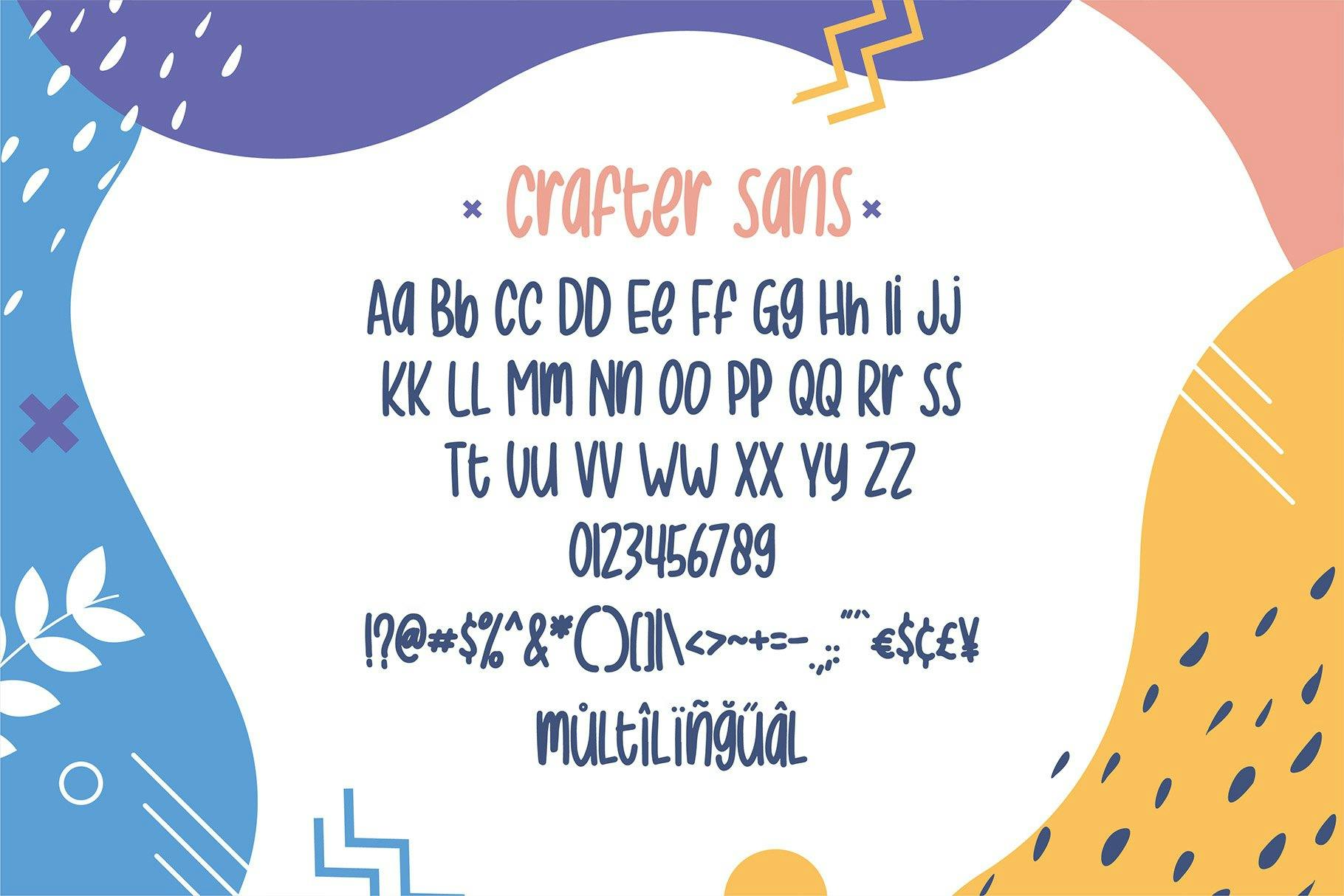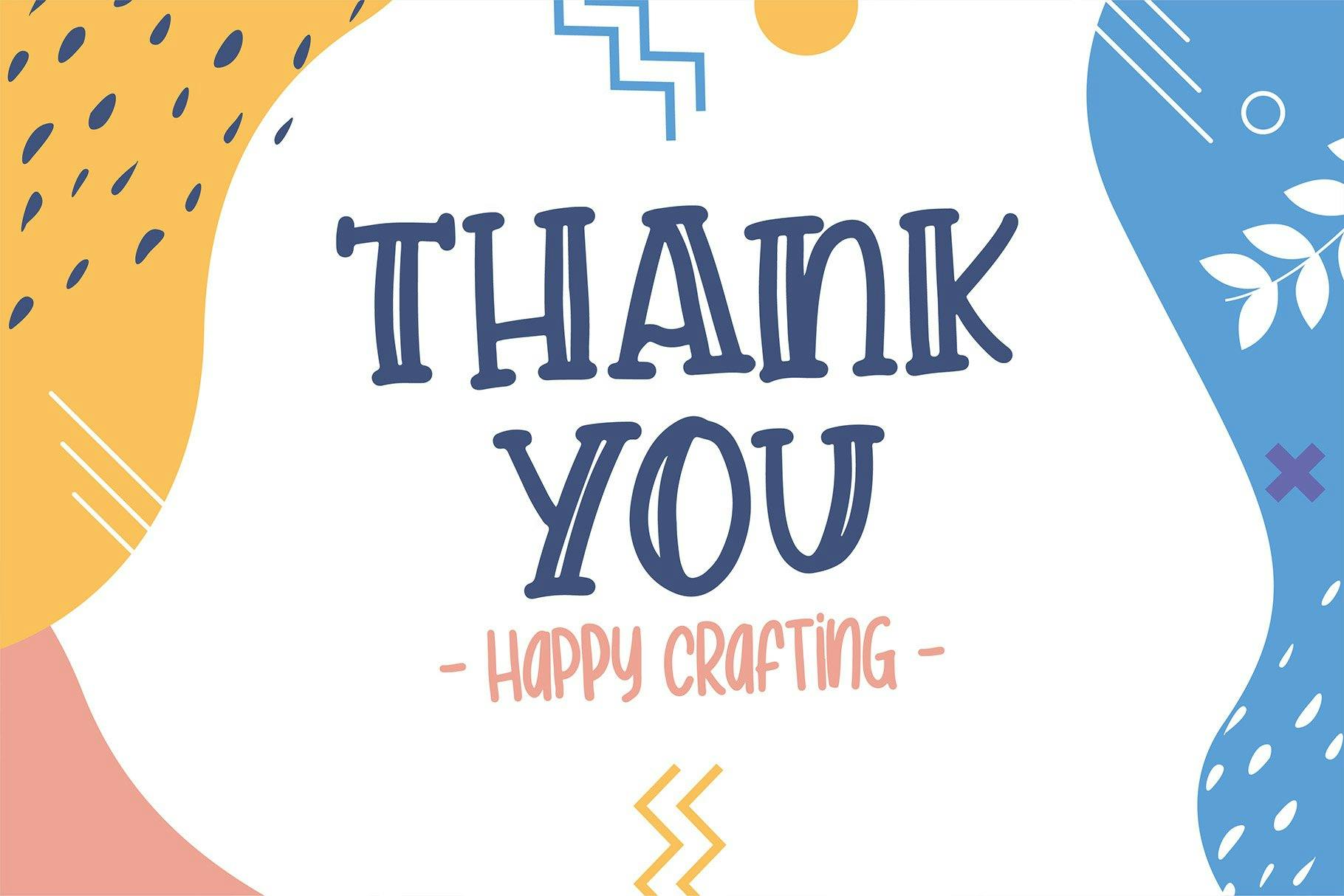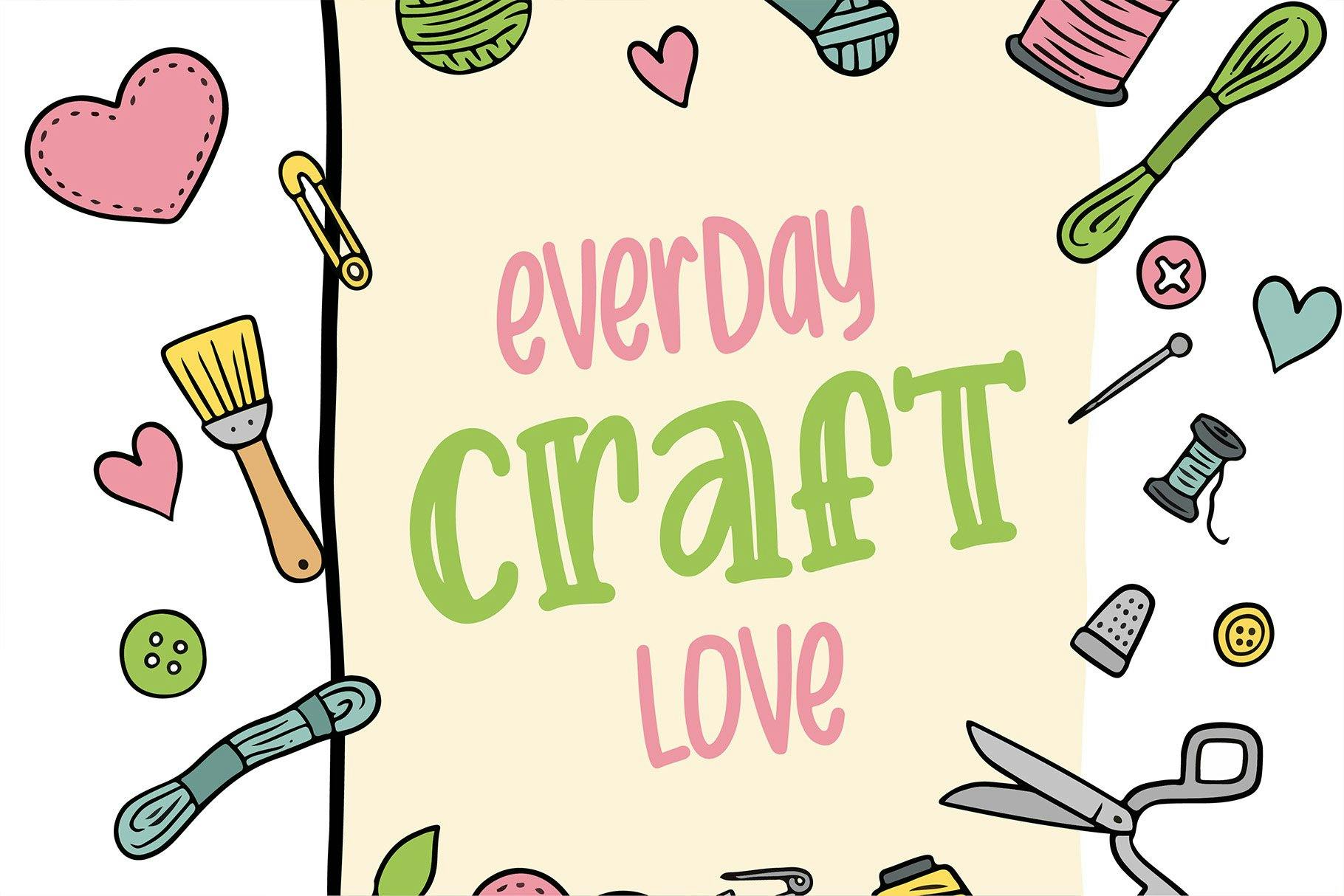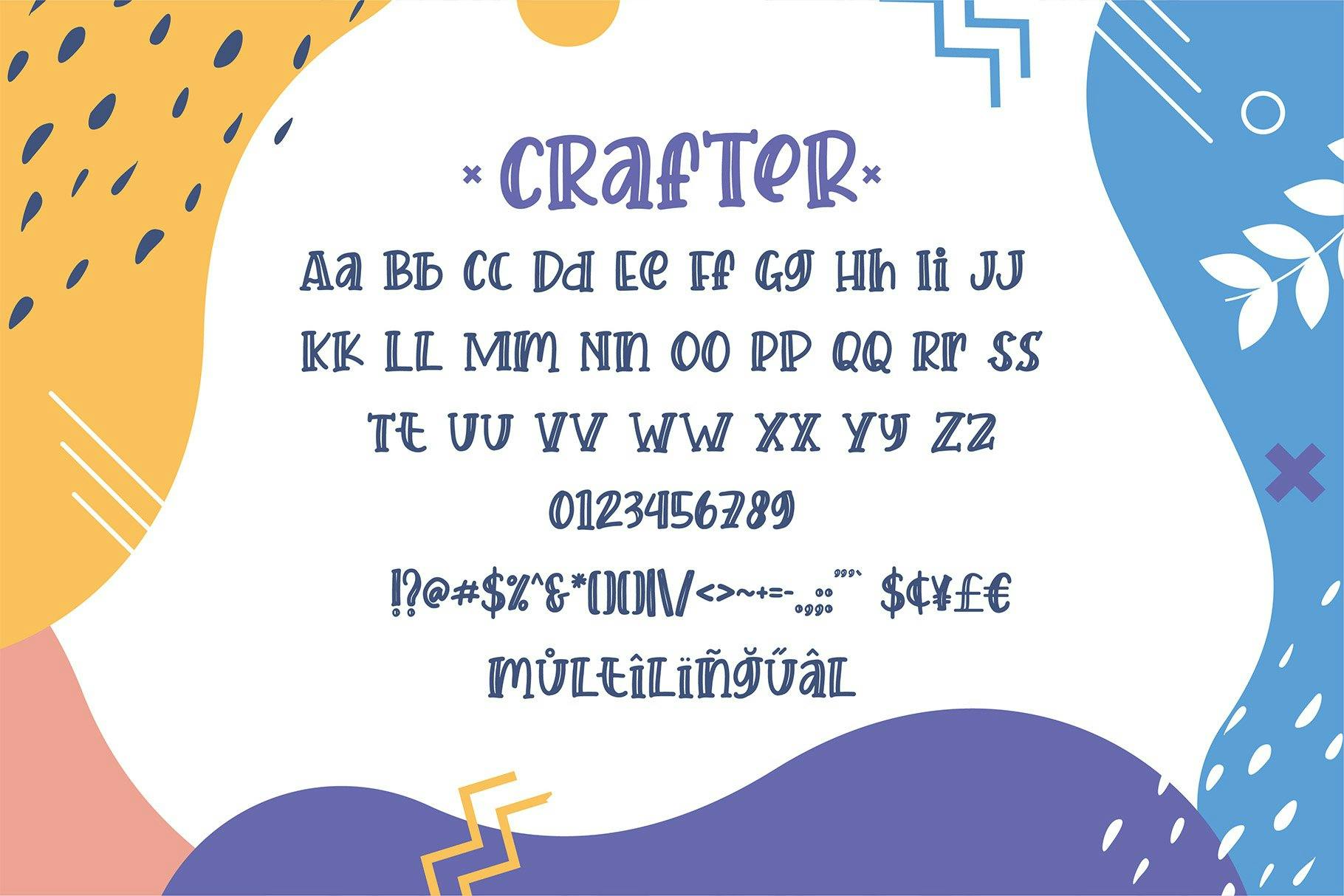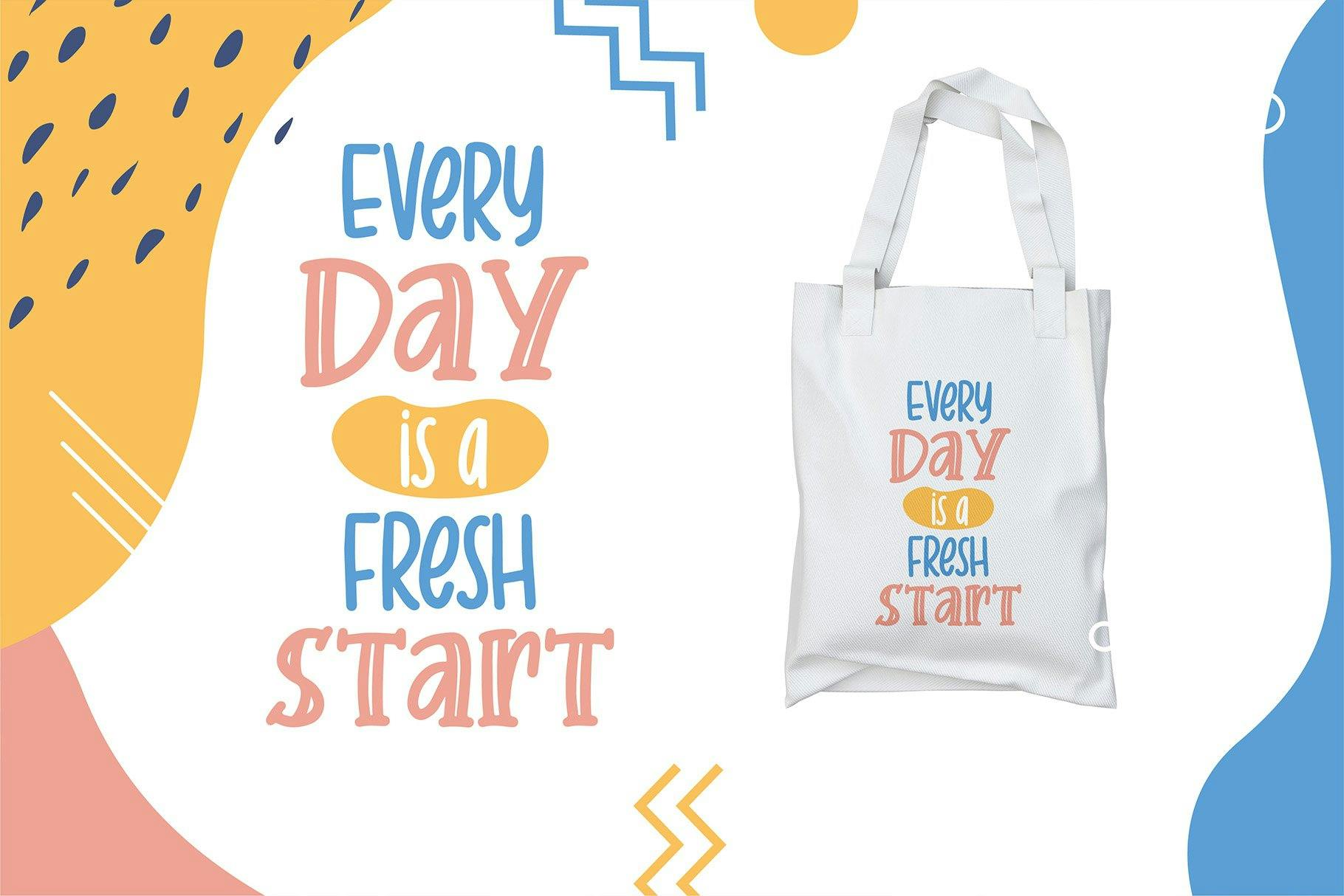
Crafter Font Duo
فونت Crafter Font Duo، انتخابی عالی برای زیباتر کردن پروژه‌های شما.
فونت Crafter Font Duo یک فونت دست‌نویس جذاب است که می‌تواند زیبایی و سرگرمی بیشتری به آثار شما ببخشد!
ویژگی‌ها:
• حروف بزرگ
• حروف کوچک
• اعداد
• نمادها
• پشتیبانی چند زبانه